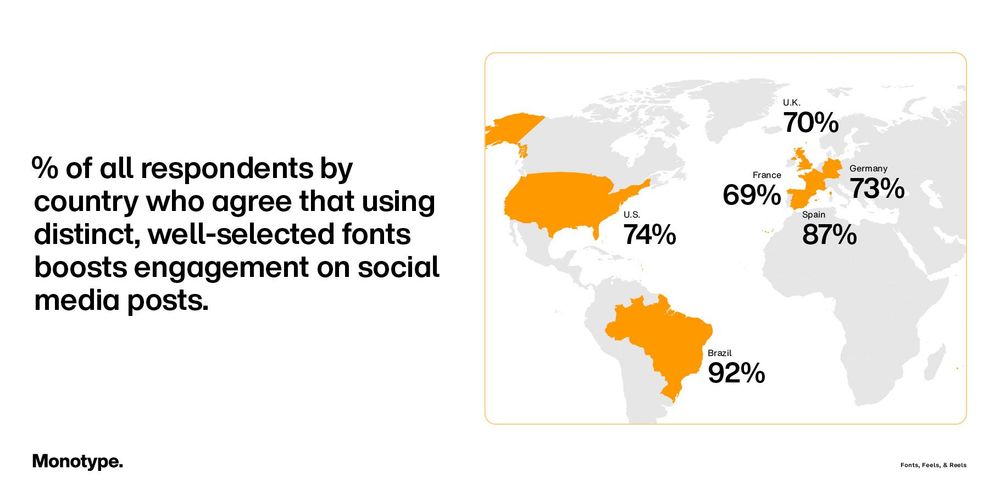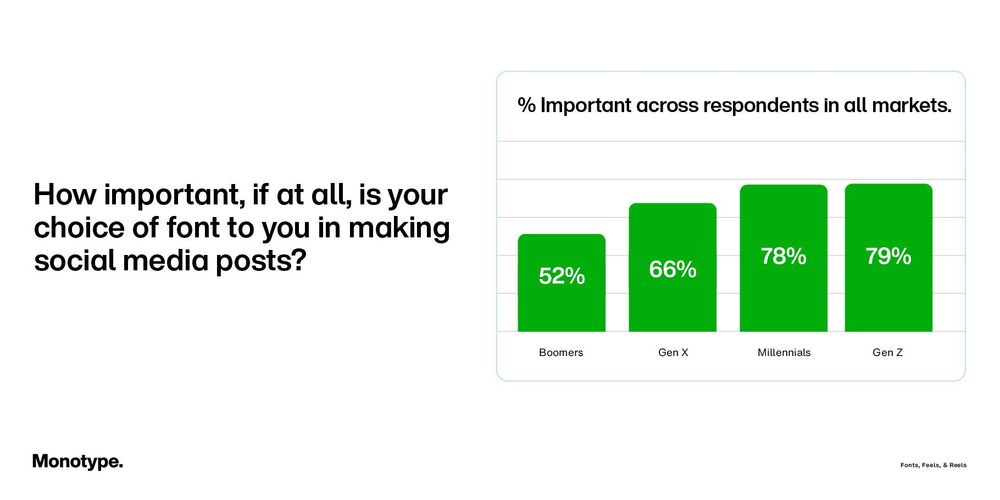
字体、情感、以及社交媒体丨蒙纳最新研究报告:各世代如何看待字体
在短视频、社交媒体和视觉表达主导的数字时代,你是否意识到:一个字体的选择,可能决定了用户是否愿意点赞、关注,甚至信任你的品牌?、
蒙纳字库最新发布报告,深入调研全球 12,000 名社交媒体用户,涵盖 Z 世代、千禧一代、X 世代与婴儿潮人群,覆盖美国、英国、德国、法国、西班牙和巴西六大市场,首次揭示字体如何成为数字身份的核心表达。
全球字体与科技领导品牌蒙纳发布其最新报告《字体、情感与社交媒体:各世代对字体的态度》的研究发现。该报告是公司持续进行的年度字体报告“Re:Vision”计划的一部分。
这项由蒙纳委托、独立研究公司 Censuswide 执行的研究,调查了来自美国、英国、西班牙、德国、法国及巴西超过 12,000 名 16 至 79 岁的社交媒体用户,揭示了各世代在社交媒体上对字体的感知与使用存在显著差异——其中 Z 世代与千禧世代最懂得字体选择所蕴含的力量。
研究显示,各世代普遍认同字体的价值,近 70% 的社交媒体用户认为字体选择对于发布帖文十分重要。这种看法在年轻的数字原生世代中更为强烈:79% 的 Z 世代与 78% 的千禧世代同意字体是发布帖文的关键要素。
根据研究结果,从 Z 世代到婴儿潮世代可以归纳出以下四大发现:
• 除了算法外,字体选择能提升参与度
78% 的受访者认同,使用独特且精心挑选的字体能有效提升帖文的点赞、分享与评论数。Z 世代与千禧世代的认同度更高,分别达 87% 与 86%,也就是说,每 10 人中就有超过 8 人肯定字体的影响力。
• 字体选择不足,年轻世代最困扰
超过半数的 Z 世代(55%)与千禧世代(52%)坦言,对常用社交平台的字体选择受限感到不满,这显示社交媒体平台在协助用户自我表达方面仍有强化空间。
• 创作者跨出平台,追寻字体自由
在使用外部设计工具制作帖文的创作者中,高达 71% 明确表示这样做是为了获得更多字体选择与控制权。这股趋势正由数字原生世代,即Z 世代与千禧世代引领。
• 字体让文字拥有情感与温度
对 65% 的 Z 世代与 67% 的千禧世代而言,字体已成为自我表达的核心要素,能直接展现个人特色、真实性与风格品味。
蒙纳执行创意总监 Tom Foley 对此现象精准诠释:“当今字体对个人表达的重要性,早已堪比衣着打扮、音乐品味与影音创作。我们的研究显示,对于从未经历过前社交媒体时代的 Z 世代而言,字体选择早已超越单纯设计考量,它们是塑造网络联结、沟通模式与创作风格的强力身份宣言。”
这项发现证实:全球不同年龄层的用户都在乎字体选择。字体从来不是静止的存在,而是会呼吸的设计媒介,它既能承载个人特色,又能塑造视觉感受,更在无形间主导着数字互动的节奏。而年轻世代对此展现出超乎常人的敏锐度,他们不仅精通如何运用字体强化表达,更懂得解读他人字体背后的潜台词。
对于消费者、品牌方、创作者、网红乃至各大数字平台而言,这无疑是一个明确的信号:字体,就是你的无声代言人。 当平台能提供丰富多元的字体选择,就等于为 Z 世代与千禧世代搭建了尽情展现自我的舞台,这不仅是抢占当代用户心智的关键策略,更是为未来全世代、全渠道的长期认同铺路。